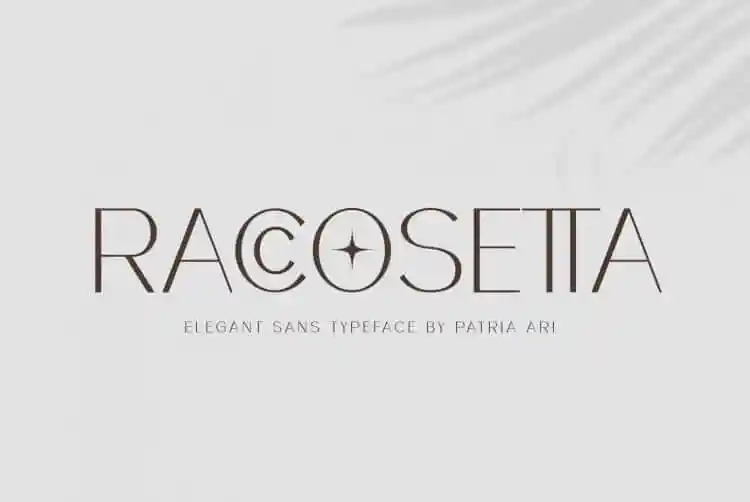
Raccosetta Sans Serif Font – Fonte Grátis
Raccosetta Sans Serif Font
A Raccosetta Sans Serif é uma fonte sans-serif leve, criada com a ajuda da Patria Ari Typestudio, que incorpora alguns detalhes adoráveis e ligaturas para dar um toque moderno e simples ao tipo. Com seu design elegante e minimalista, esta fonte idealmente se ajusta às aplicações de mídia em cartaz, headlines, convites casamento, logotipos e templates de PowerPoint, tornando-a uma opção perfeita para aqueles buscando um estilo fresco e moderno que seja ao mesmo tempo amigável e poderoso. Não importa se você está criando um design imponente ou algo mais leve, a Raccosetta Sans Serif tem tudo o que precisa para deixar sua marca registrada em qualquer projeto gráfico. Ela é uma escolha perfeita para designers que buscam um tipo versátil e desafiador, capaz de se destacar na tela sem perder seu encanto elegante.